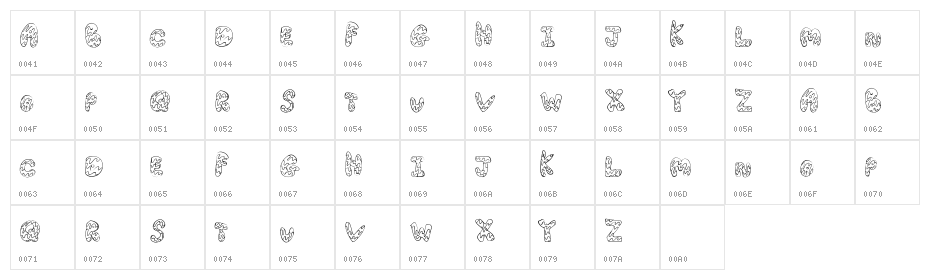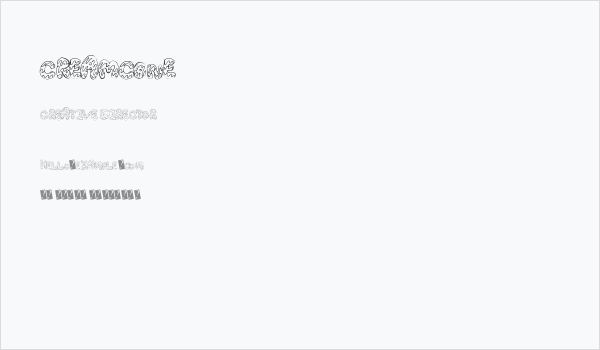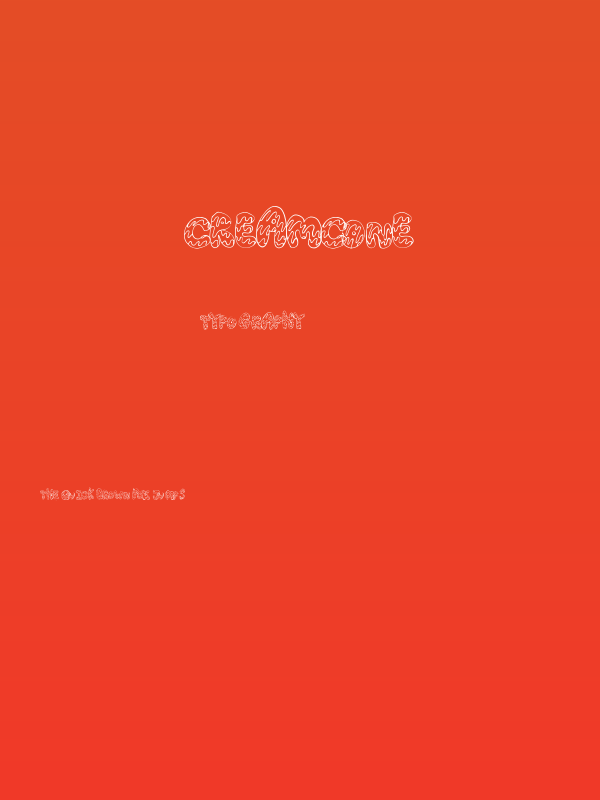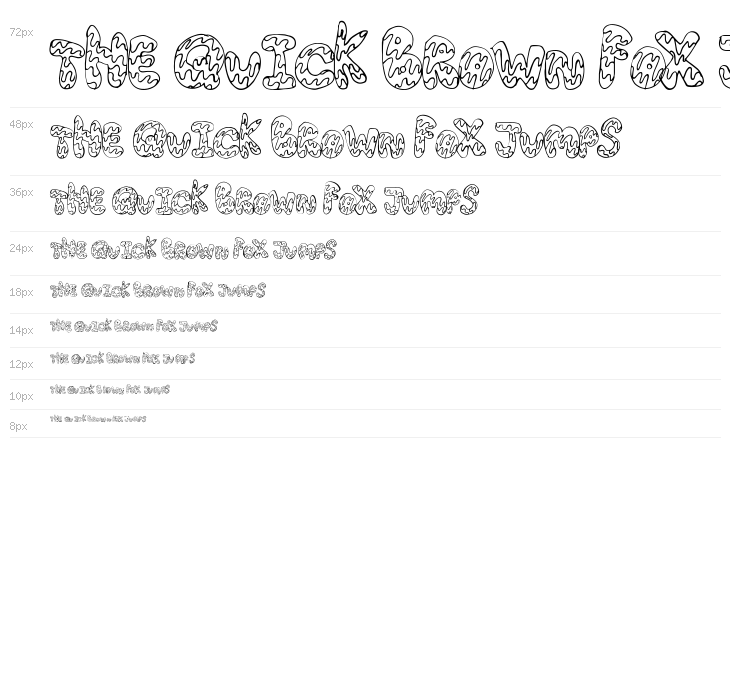
CreamCone Font
| Stile generale | Whimsical |
| Progetti proposti | Ideal for children's book covers, ice cream shop branding, summer event posters, and playful social media graphics. |